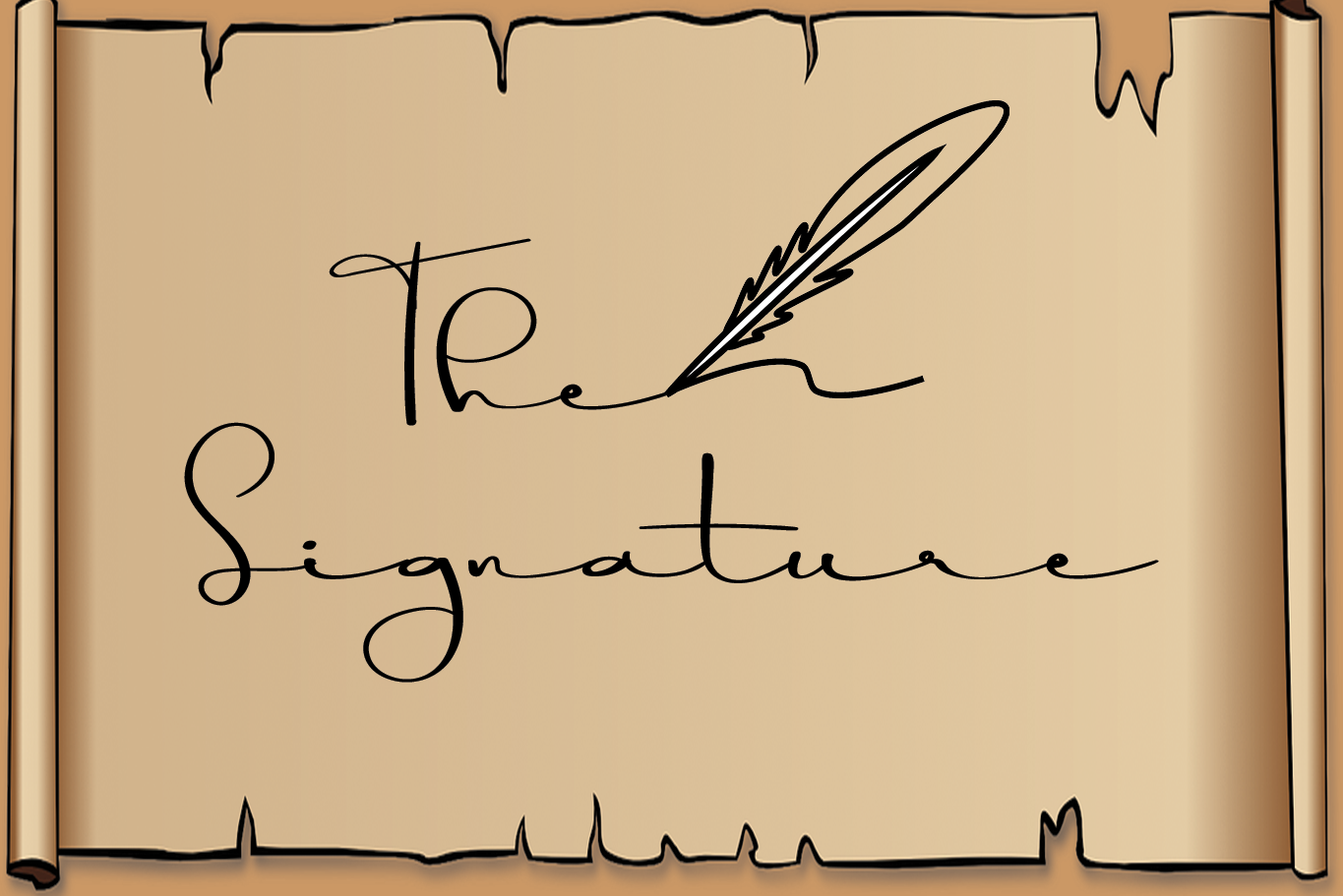
Esta é uma fonte script delicada que transmite beleza e poesia. Ela é perfeitamente apropriada para projetos elegantes como cartões de aniversário, convites de casamento, cartões de negócios, citações e mais. Sua facilidade de uso permite transformar qualquer projeto em algo único e inesquecível. Seja para uma cerimônia especial ou um evento memorável, The Signature Font oferece a perfeita combinação de elegância e criatividade. Inspirado pelo estilo do desenho à mão, esse design foi cuidadosamente criado por Erik Studio, garantindo que cada detalhe seja perfeito para suas necessidades criativas.